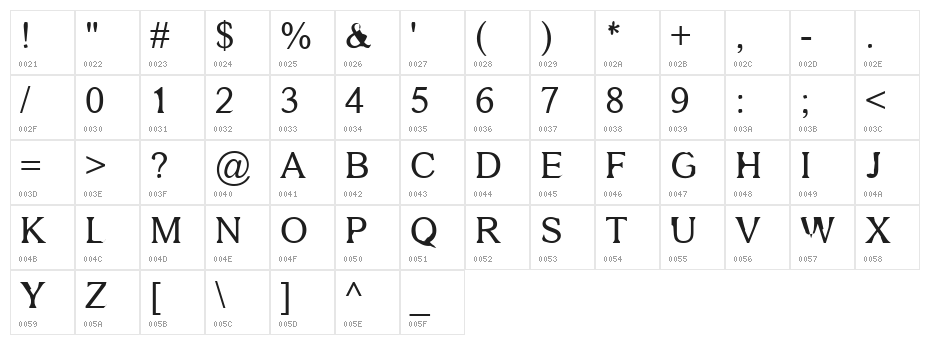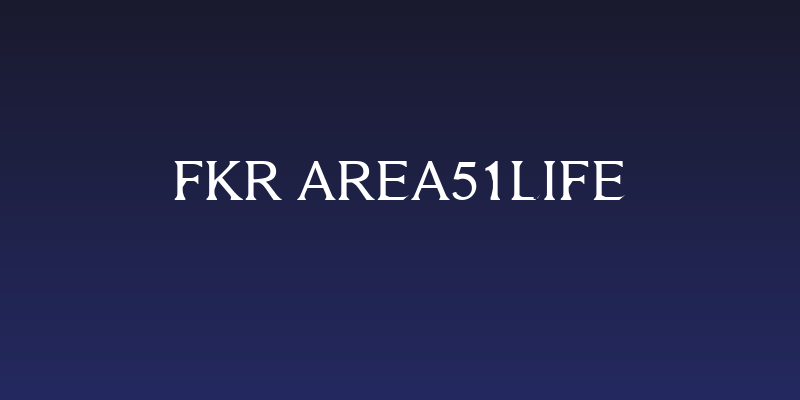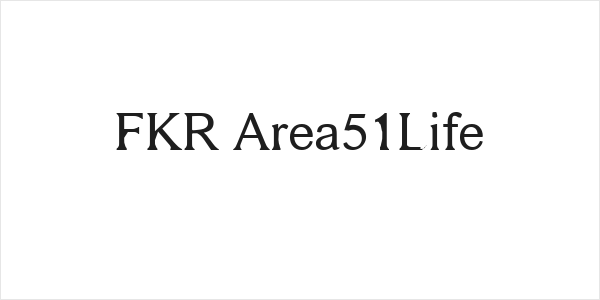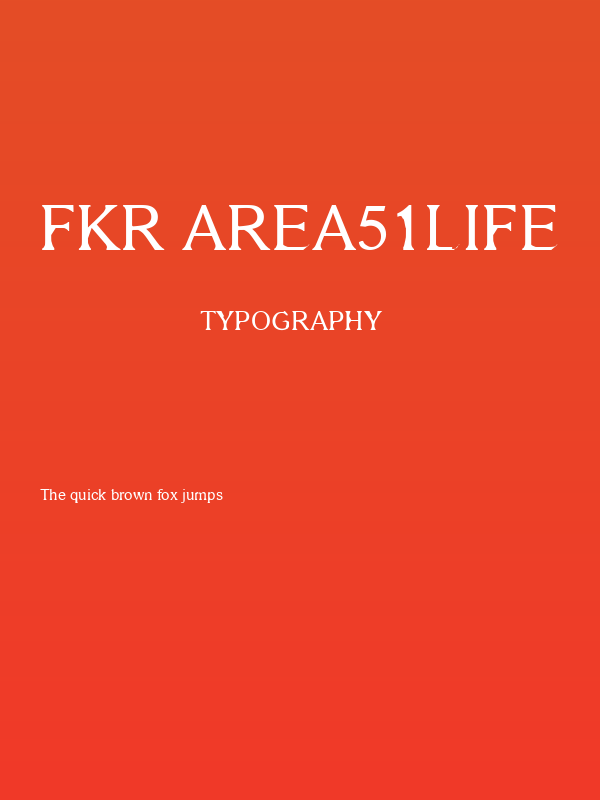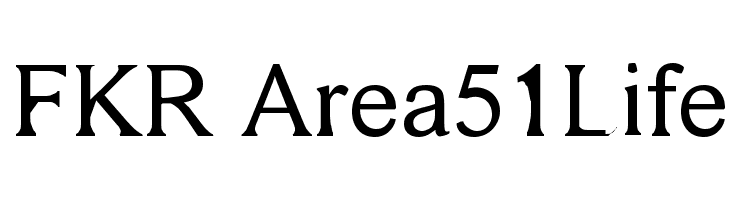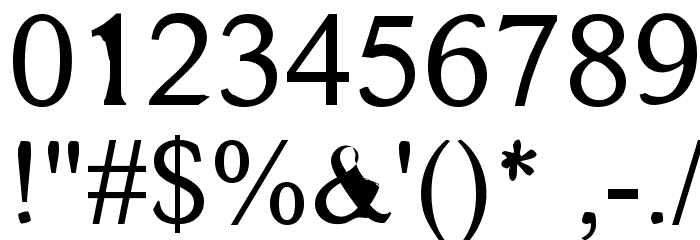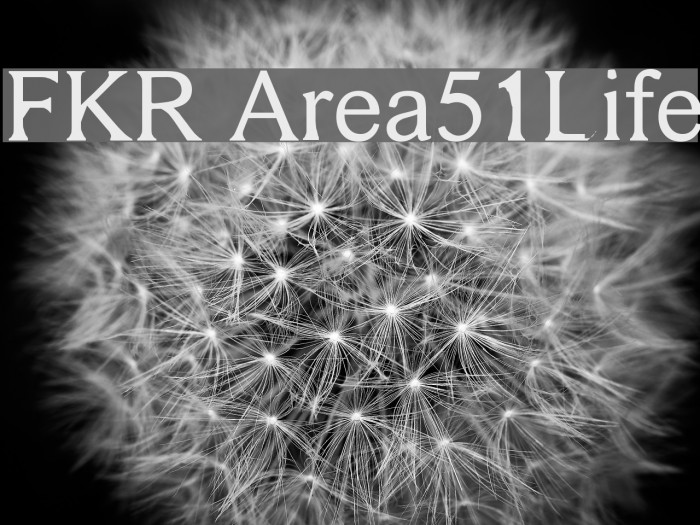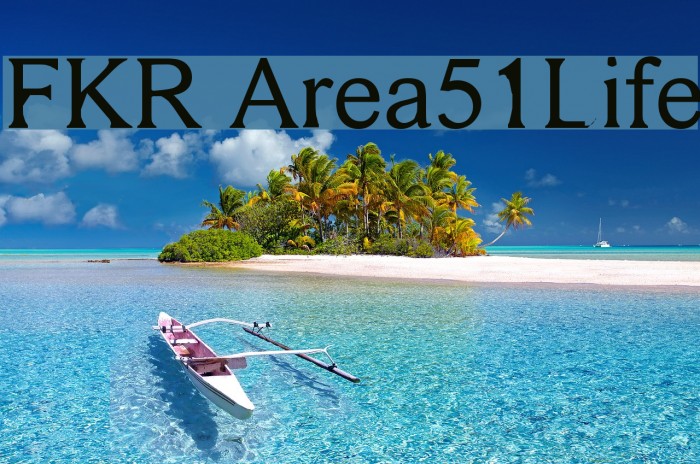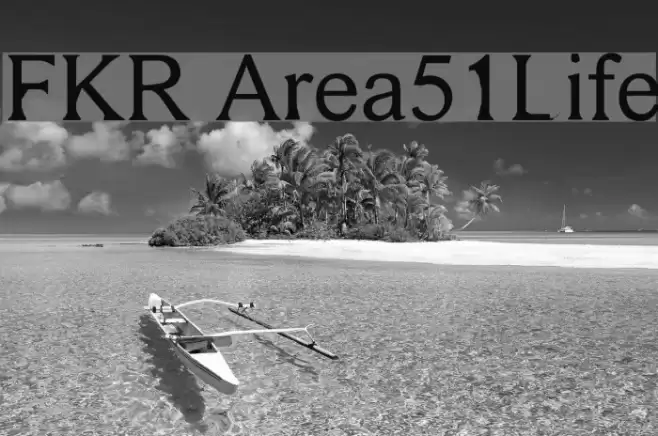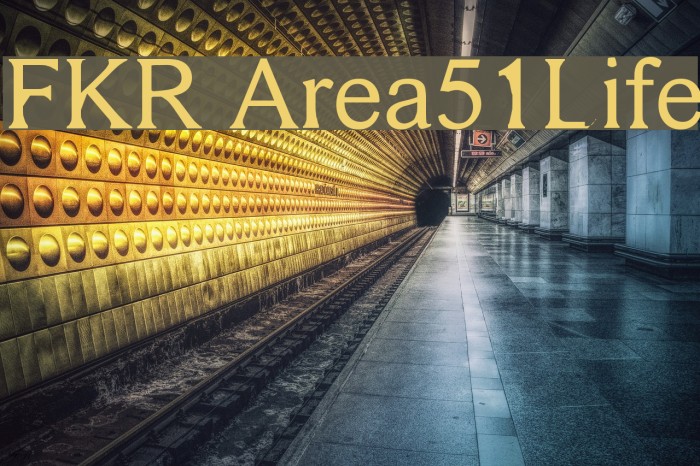
FKR Area51Life Font
| Kategorien | Formal |
| Gesamtstil | Classic |
| Anwendungsfall | Headlines, Body text, Logos |
| Vorgeschlagene Projekte | Ideal for book covers, formal invitations, branding materials, and editorial design. |